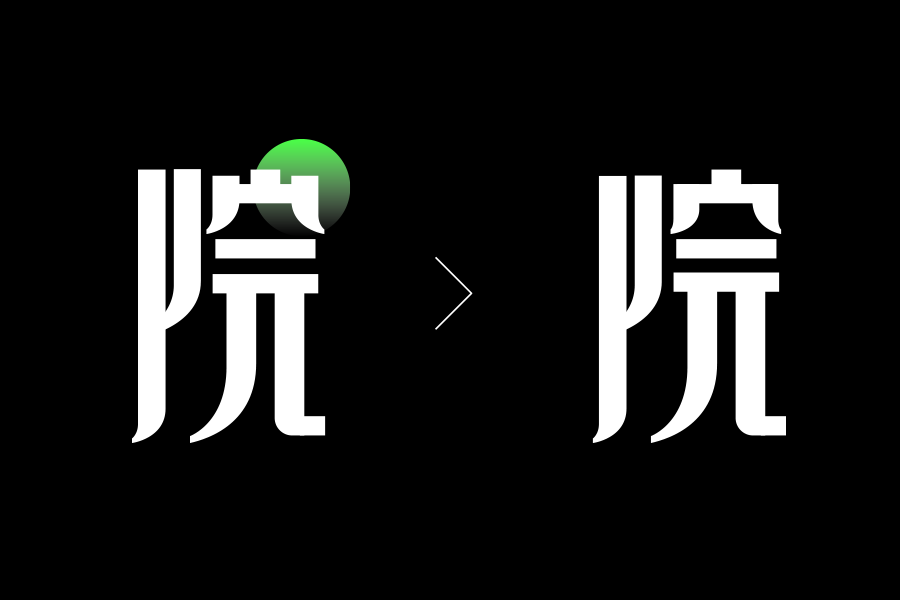
改字就像是一个半命题作文,材料给到了我会尽量叙事好。帮大家改字不是全部推翻重来,这样没有太大意义,我会尽量维持原有字体方向,解决主要矛盾,帮大家理清思路,并拓展一些小知识点。如果觉得改字中有不妥之处,欢迎留言讨论。
本期选一组比较特殊的字,说特殊是因为其背后或许代表了一群初做字体的朋友。即便现在关于字体设计的书籍、视频、教程很多,但是还是会有很大一批同学在刚刚接触字体设计时无从下手,问题频出。正如上图原稿字体,能看得出有很多‘章法’在里面,比如最明显的竖笔起笔的斜切处理做了统一,再比如整体结构也做的瘦高有变化,可是似乎还是存在比较多明显的问题,最直观的感受如果用大白话讲就是:不好看!看一些字体字体教程文章的时候大家会发现,每家的说法都不太一样,每个人的观点也会有不同,甚至有很多矛盾点,这会让很多新手蒙圈。设计的世界很难分清对与错,矛盾对立不可怕,重点是大家要学会平衡。统一与变化看似矛盾其实并不冲突,他们更像是整体与局部的关系。上图中注意笔画粗细的变化,尚字内部的‘口’笔画明显要比大部分笔画细,作者可能是基于这样的一个理论:字体笔画外粗内细。凡事有度,处理得太细直接导致笔画粗细的失衡,周围空间的大面积留白,会直接导致视觉上这个局部的‘弱势’,所以这个变化是有问题的。统一不是没了变化,原稿字中作者把所有的笔画统一处理,有曲度变化的笔画也全部统一成横平竖直,放在某些局部这样做是可行的,如‘阝’部的处理,可是‘院’字最后撇和竖弯钩在这样处理不免就有些刻板了。一些奇奇怪怪让人不理解的‘变化’毁掉一个作品。上图是放大‘院’字的细节,竖线的倾斜、点的形式变化未免太随便了,不像是变化更像是设计上的失误。听听一颗铁钉的故事:"少了一个铁钉,丢了一只马掌;丢了一只马掌,翻了一匹战马;翻了一匹战马,败了一场战役;败了一场战役,失了一个国家。"东西多不代表画面更丰富。做最后的排版时,元素之间的对比、融合都需要精密配合,不必要起不到作用的元素不强留!原稿中主题字周围又加了一个细细的矩形框是几个意思?我只能放出一个表情来表达我此刻的心情。
主体字右边的元素单独看还有些节奏感,但如果整合到一起就会发现两个比较明显的问题,一个是上下和细框对齐导致右下角拼音有点托底;二是‘名流府邸 至臻至尚’这几个字选取的字体过细,与主体字重量失衡。原字的竖笔收笔的处理是适合这组字的,一开始想的是完全留住,如上图居中的效果,有感觉过于冷静,所以又做了点调整如上图最右所示。结构上依然是保留原有比较瘦长的一个状态,但之前内部留白过多,这里再去调整时适当收缩,整体看起来会更加紧凑。断笔是很常见的处理手法,但要注意不要把整体的字给打散了。比如‘阝’的处理,原字基本上就是两条竖线了,过于简化,所以我把下面弧度加大使之与左竖线连接,整体性会更好些。继续看‘院’字的处理,明显的一个变化在于撇和竖弯钩,之前说过这两点的问题,具体就不再多说了。左边是最初修改的样子,但觉得‘宀’会有些琐碎,后面又调整成右边横竖平齐的状态。修改到这一步基本就定调了,但觉得个性不够凸显,有添加了一些小的修饰和变化,看上图左右对比。上图是中文字的放大轮廓,下面我们再去解决一下排版的问题。排版对于很多新手来讲是个老大难的问题,下面我从上到下说下选择的理由。首先是这个图章,原稿的图章是一个椭圆加上‘尚院’两个宋体字,两个字评价:简陋!尤其在缩小的情况下,里面两个字简直要用下放大镜。我直接借用印章中‘尚’字写法的写法,用钢笔工具勾出线段即可。中文宣传语前面说过问题了,太轻太弱,所以就找找有点传统韵味又有点分量感的就搞定啦。再看拼音的选择,还是明显感受到那种选择的随便,最简单的根据主体中文字的特性来找英文,瘦高、有衬线装饰、比较庄重、横细竖粗...总之,不!要!太!随!便!下面是最终稿的对比,颜色直接选用了黑色,印章为朱红,居中对齐方式会突出重点更有气势,所以排版也没‘耍花样’,过多的变化并不适合这个主题。本指南不会给大家罗列一大堆零零总总的东西,通过一个小白做的一个字分解开来,希望各位同学能够各取所需,开卷有益。本期就跟大家聊到这,如有未尽,下期再会